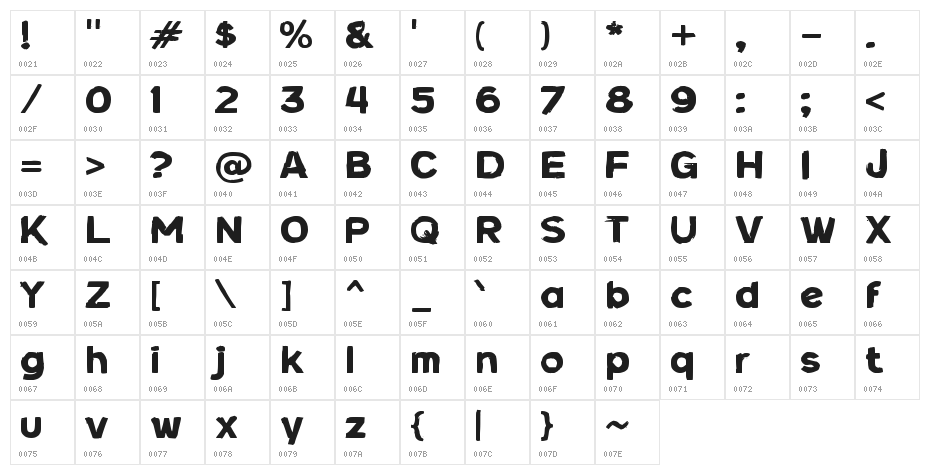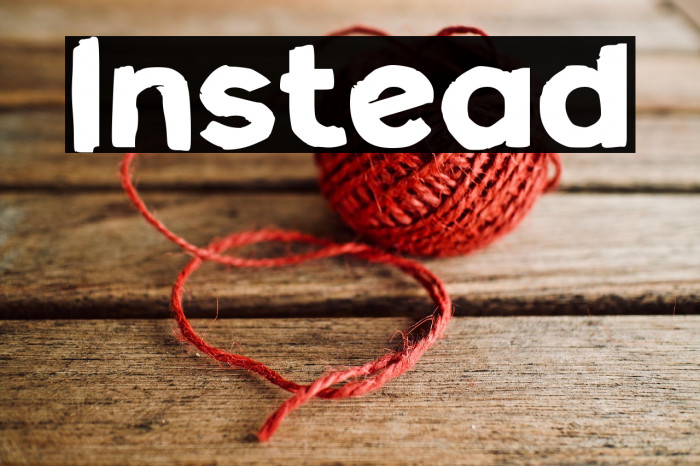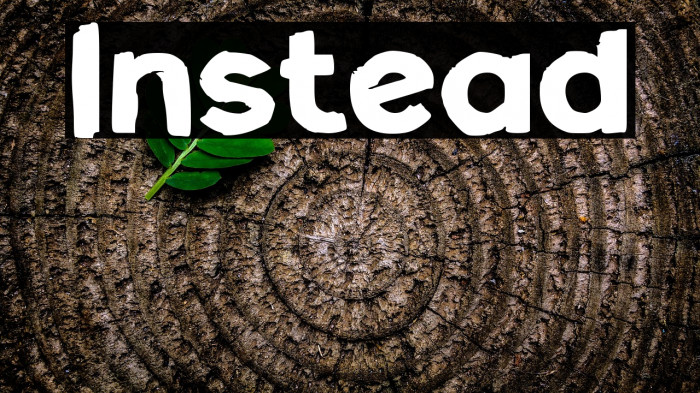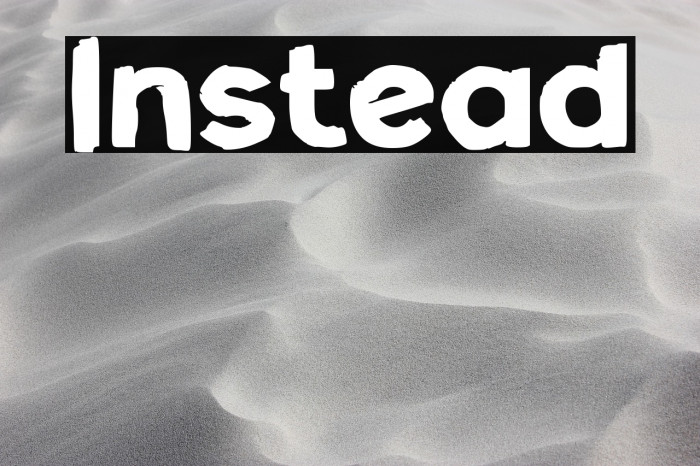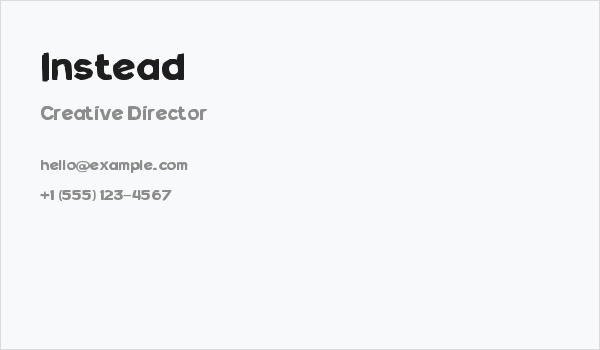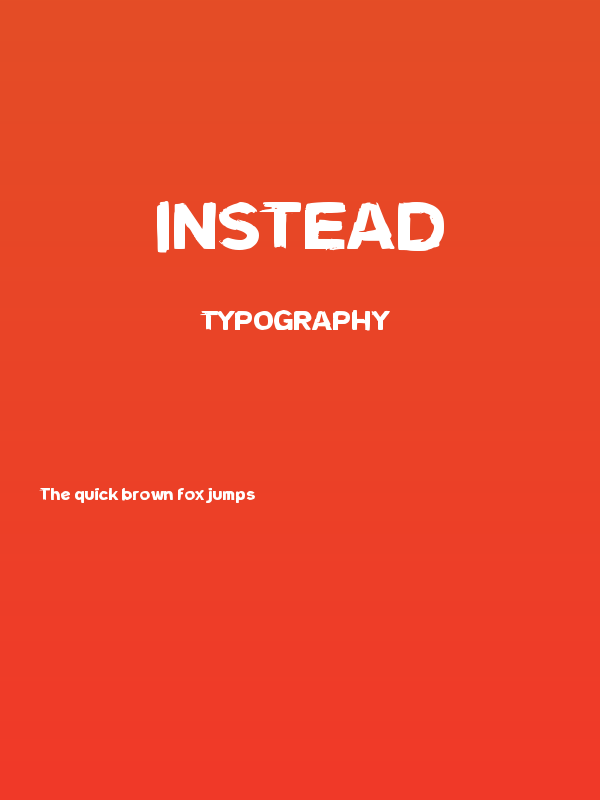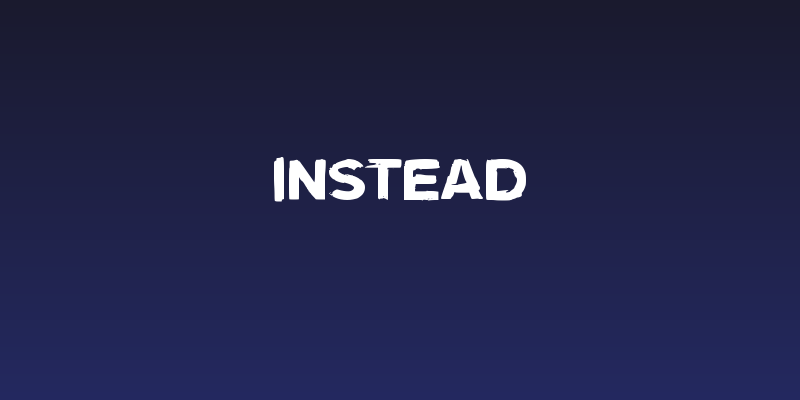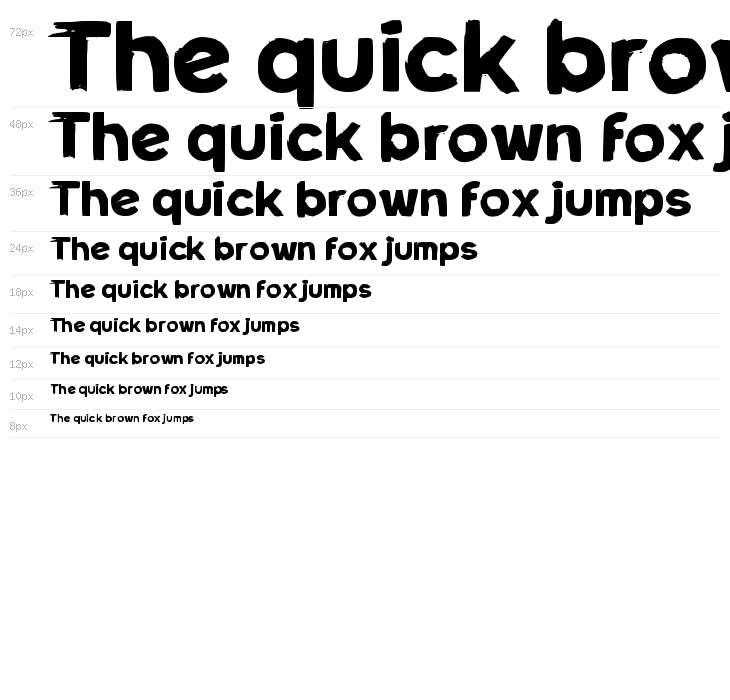
Instead Font
✎ Thick
| Vorgeschlagene Projekte | Ideal for posters, branding, packaging, and artistic projects that require a bold and expressive typeface. |